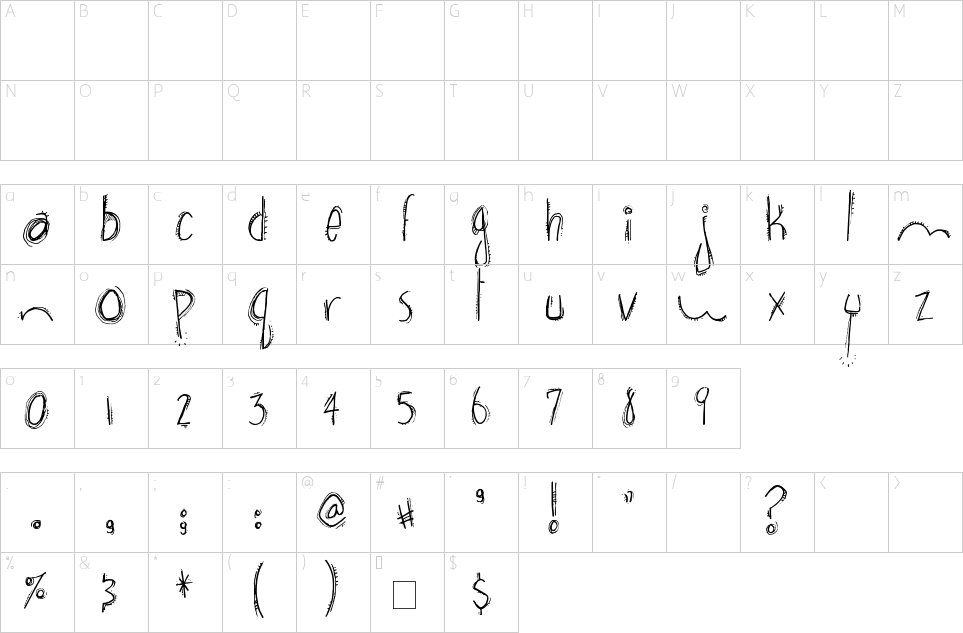
Descubra a fantasia visual da fonte Brown Bear Funk, uma opção elegante para adicionar um toque único a suas criações digitais. Inspirada num urso branco que ilumina o inverno, esta fonte traz um toque de graça e humor. Desenvolvida pela Segments Design FKA Last Soundtrack, a Brown Bear Funk foi projetada para aqueles que valorizam a criatividade e a diversão no design. Se você está procurando por uma fonte divertida e original que irá destacar seus projetos, a Brown Bear Funk pode ser a escolha certa. Este download é uma ótima maneira de adicionar um elemento divertido e único aos seus materiais digitais. Com seu design único e fácil de usar, a Brown Bear Funk é uma escolha perfeita para designers e criativos de todos os tipos. Se você está procurando por uma fonte que traz um pouco de diversão ao seu trabalho, a Brown Bear Funk pode ser a solução perfeita.